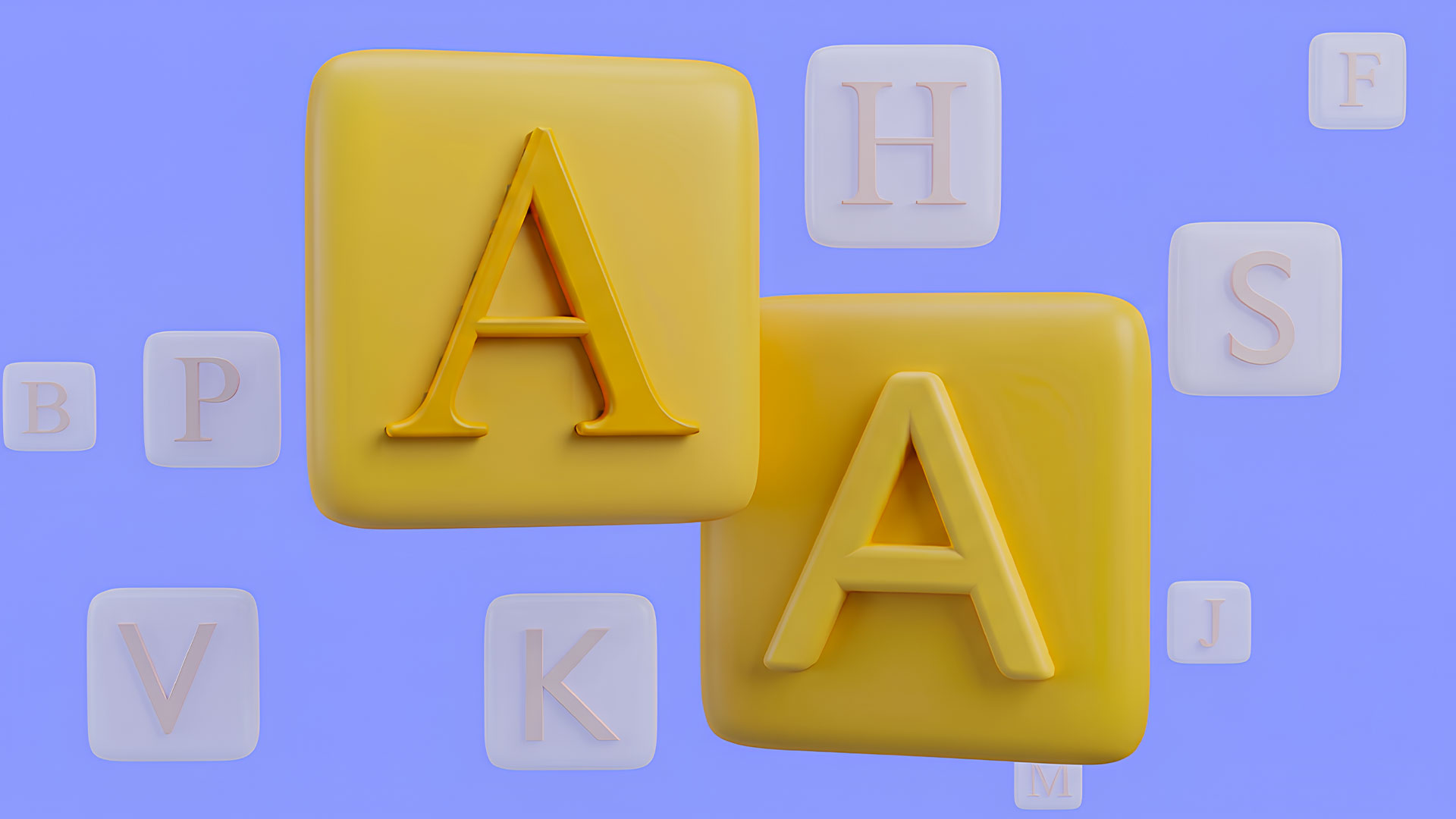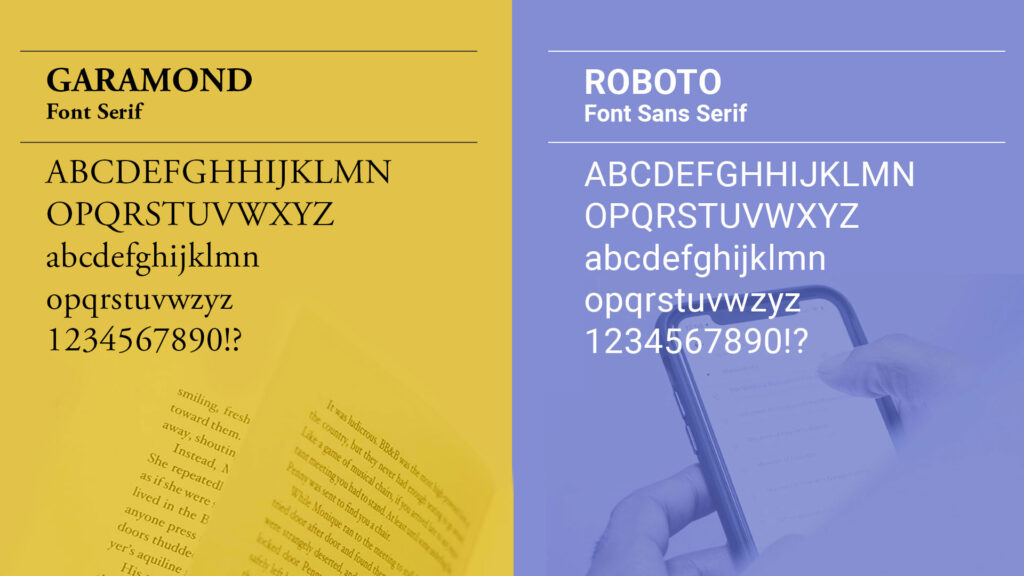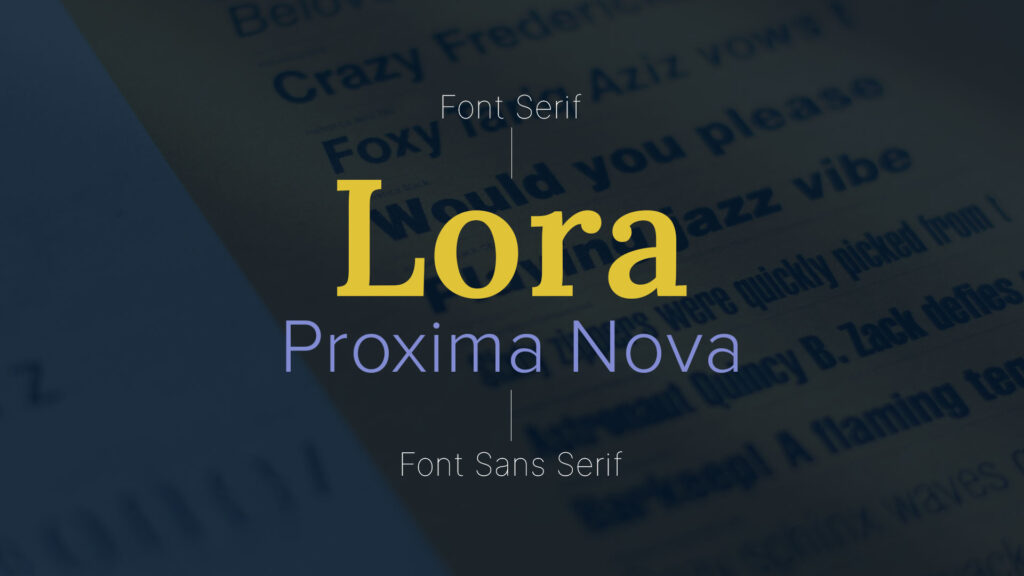
Font serif e sans serif: differenze, caratteristiche e quando scegliere l’uno o l’altro
Due lettere A tridimensionali gialle, una con le grazie e una senza, fra altre lettere sullo sfondo
Qual è la differenza tra un font serif e un font sans serif? E soprattutto, quale scegliere per un logo, un sito web o la brand identity della propria azienda?
La tipografia è uno degli elementi più importanti della comunicazione visiva. La scelta del carattere tipografico non influenza solo l’estetica di un progetto, ma anche il modo in cui un brand viene percepito dal pubblico. Un font può trasmettere autorevolezza, eleganza, innovazione o semplicità ancora prima che il lettore inizi a leggere il contenuto.
Per questo motivo, scegliere il carattere giusto non è una semplice questione di gusto, ma una decisione strategica che incide sulla leggibilità, sull’esperienza utente e sull’identità visiva del marchio.
Esistono migliaia di font, disponibili sia online sia offline: basti pensare alle librerie di Google Fonts o Adobe Fonts, ma anche ai caratteri personalizzati che possono essere creati a partire da una calligrafia originale. Per orientarsi in questo universo tipografico è utile partire dalla distinzione più importante: quella tra font serif e font sans serif.
In questa guida scoprirai cosa caratterizza queste due grandi famiglie tipografiche, quali sono le loro differenze, quando conviene utilizzare l’una o l’altra e come scegliere il font più adatto in base agli obiettivi del tuo progetto di branding, graphic design o web design. Bonus: ti mostreremo anche come noi di ELAN42 applichiamo la tipografia nei nostri progetti di branding, sviluppo web e digital design per il marketing.
Cos’è un font e perché è importante nella tipografia?
Prima di confrontare le due principali famiglie tipografiche, è utile chiarire un concetto fondamentale: che cos’è un font?
Un font è l’insieme dei caratteri tipografici che condividono lo stesso stile grafico. Ogni font appartiene a una specifica famiglia tipografica, caratterizzata da forme, proporzioni e dettagli che contribuiscono a creare una determinata personalità visiva.
Per questo motivo il font rappresenta una componente fondamentale della brand identity. Un carattere ben scelto rende un marchio riconoscibile, migliora la leggibilità dei contenuti e contribuisce a creare un’esperienza coerente su tutti i canali, dal sito web ai social media, fino ai materiali stampati.
Cos’è un font Serif? L’eleganza della tradizione
I caratteri serif o, anche detti graziati sono contraddistinti da una piccoli elementi decorativi posizionati sulle estremità delle lettere, detti per l’appunto “grazie”.
Questi caratteri hanno radici storiche lontanissime, risalenti agli anni dell’impero romano: basti pensare alle iscrizioni lapidarie realizzate a scalpello. L’esempio più famoso al mondo  di font serif dell’antichità è senza ombra di dubbio la base della Colonna Traiana a Roma.
Proprio per il loro passato, associamo ai font graziati un senso di tradizione ed autorevolezza, oltre che lusso e raffinatezza dei decori.
Esempi famosi di font graziati che avrai sicuramente sentito nominare sono il Times New Roman, il Garamond e il Georgia. Come Digital Agency con più di 10 anni di esperienza accumulata nel settore, non possiamo non nominare i font Bembo e Jenson, nati proprio a Venezia.
Dal punto di vista della leggibilità, le grazie svolgono una funzione pratica: creano un’ulteriore linea immaginaria orizzontale che aiuta l’occhio umano a scorrere lungo le righe, rendendo la lettura di paragrafi lunghi estremamente naturale. Noi di ELAN42 teniamo sempre a mente questo trucchetto quando diamo vita alle nostre brochure aziendali o altri impaginati di questo genere. Fai un test, apri un libro e facci caso, probabilmente sarà scritto con un font graziato!
Confronto fra un font serif, il Garamond, e un font sans serif, il Roboto
Cos’è un font Sans Serif? Pulizia e modernità digitale
Al contrario, i caratteri sans serif o, tradotto dal francese “senza grazie” , sono privi di elementi decorativi. Si presentano come linee pulite e molto e geometriche, sono per questo anche detti “font bastoni”. Nascono durante la Rivoluzione Industriale in Inghilterra, con la necessità di far conoscere al pubblico tramite pubblicità il sempre crescente numero di nuovi prodotti, eventi e servizi ferroviari. Questi font con il passare degli anni e con l’esplosione del web si sono oggi confermati come prediletti nelle piattaforme online.
Tra gli esempi famosi più diffusi possiamo citare Helvetica, Futura, Arial, Roboto e Montserrat. Se sei interessato proprio qui trovi una guida alla scelta dei migliori Font per il Web.
Sia visivamente che idealmente i caratteri sans serif, senza “fronzoli” arrivano dritti al punto, trasmettono immediatezza, trasparenza, minimalismo e modernità. La loro forza strategica risiede nella perfetta resa sulle interfacce digitali: sui monitor di computer e smartphone, dove le risoluzioni o le dimensioni ridotte dei pixel potrebbero sgranare i dettagli più piccoli delle grazie.
Che tu stia progettando un logo, un sito web, un e-commerce o una nuova identità visiva, la tipografia contribuisce in modo concreto alla percezione del tuo marchio e all’efficacia della comunicazione.